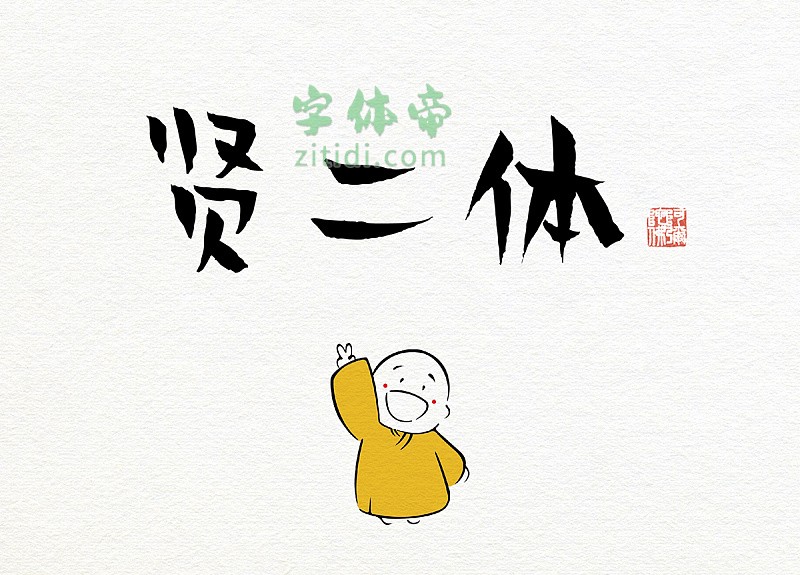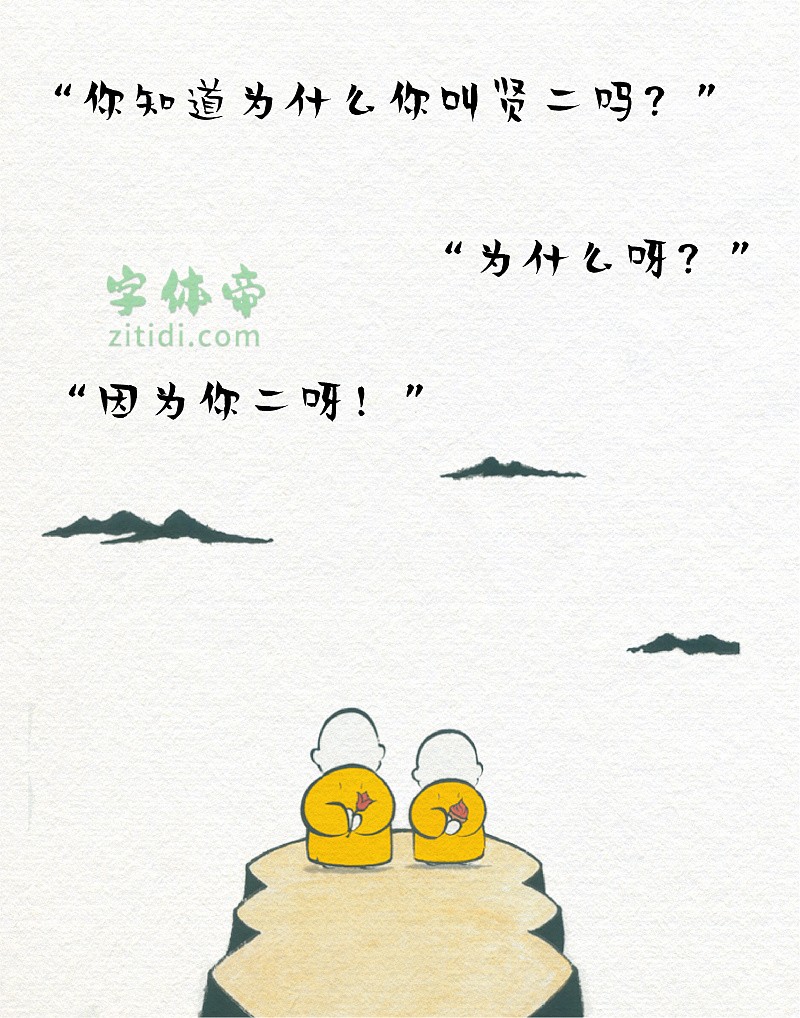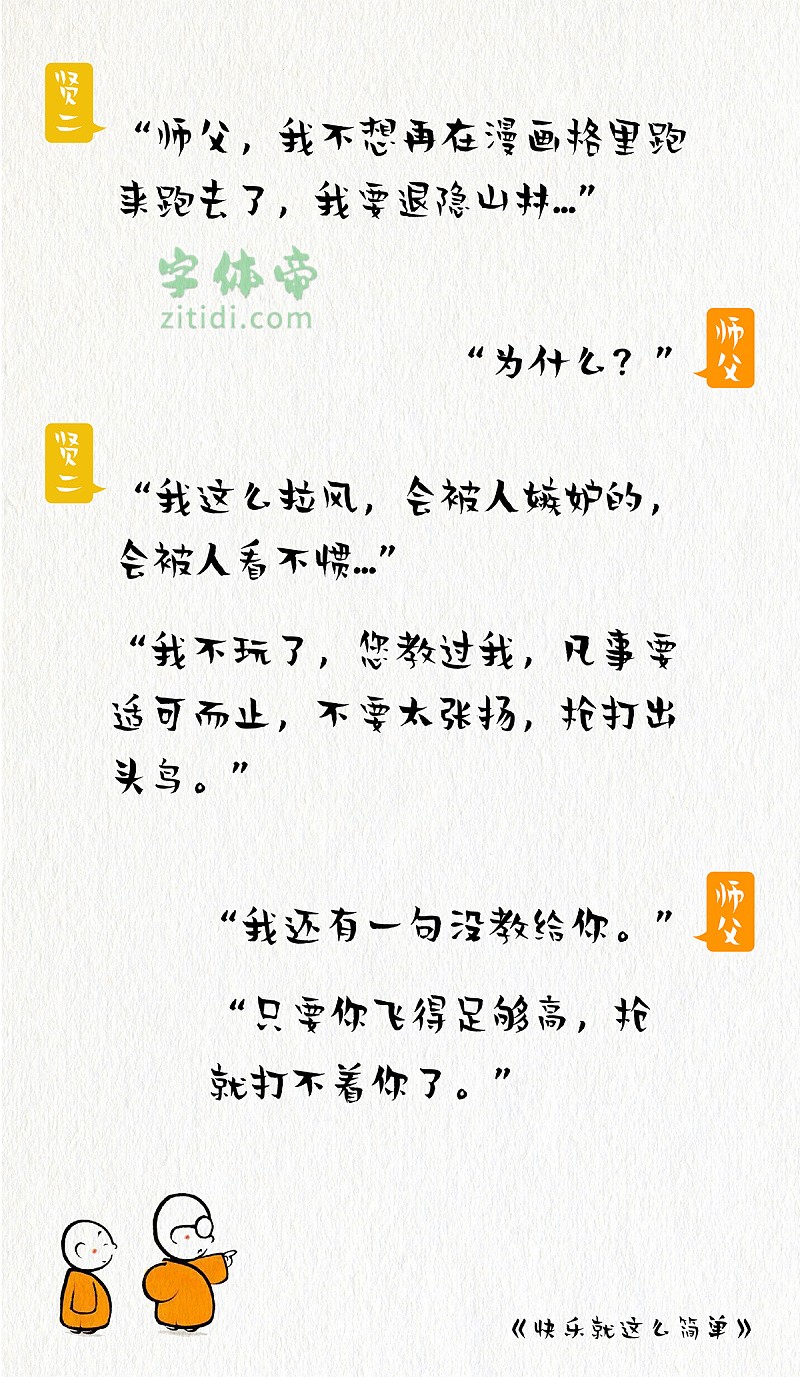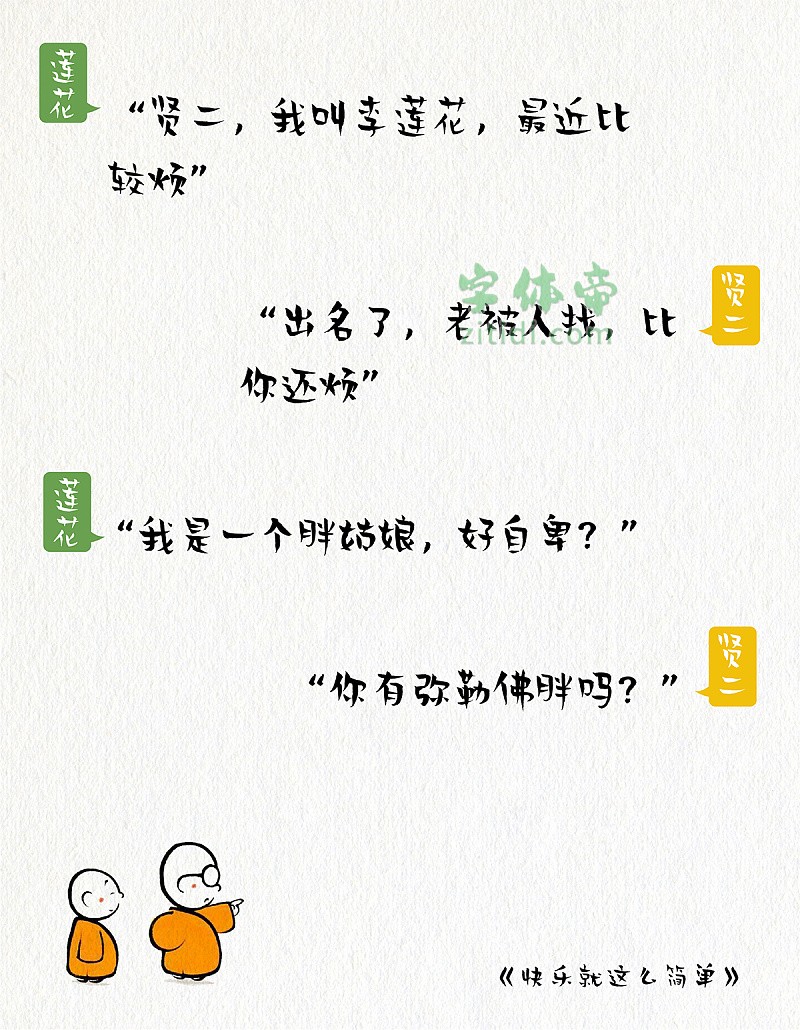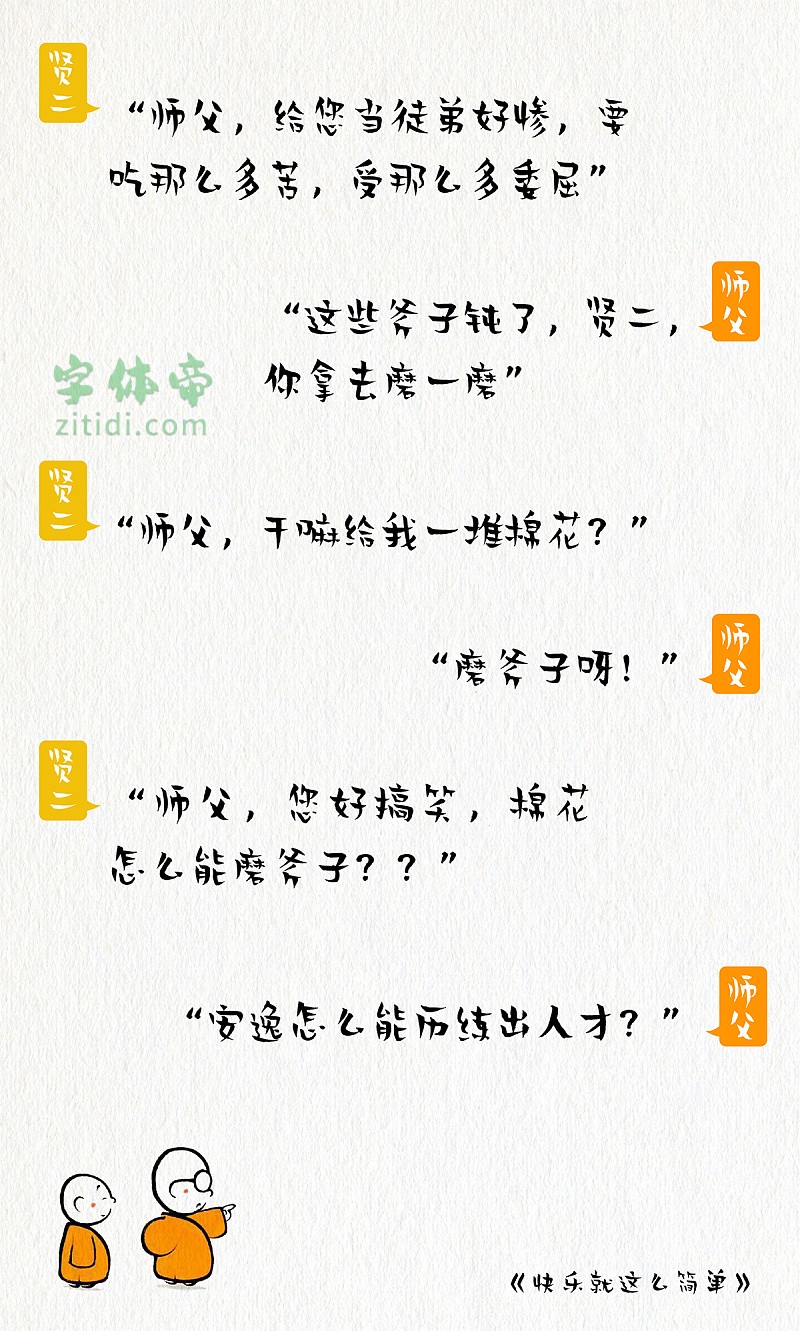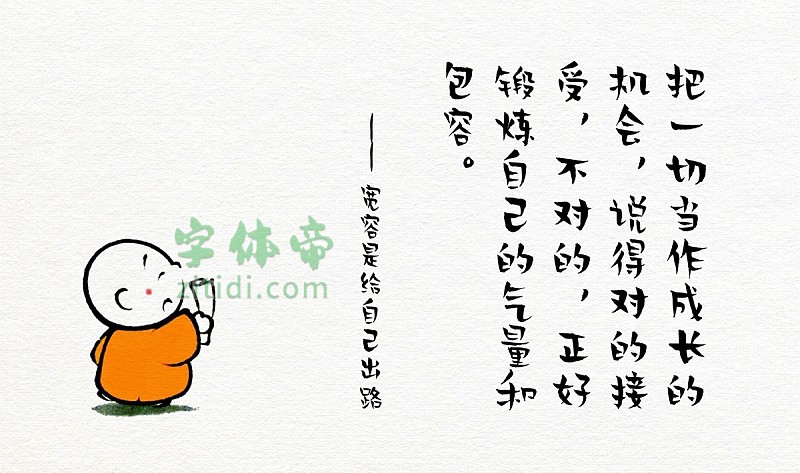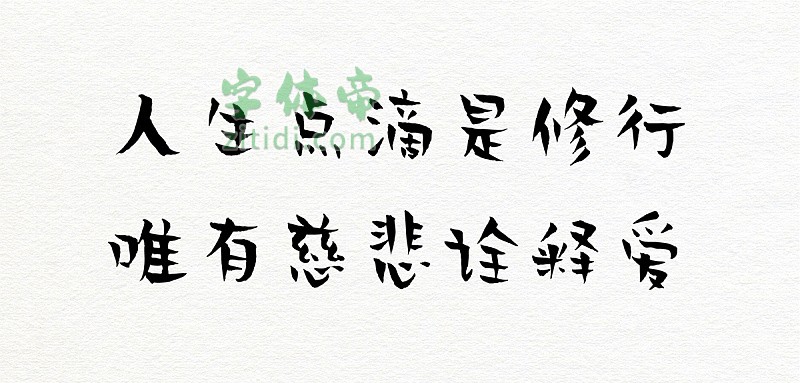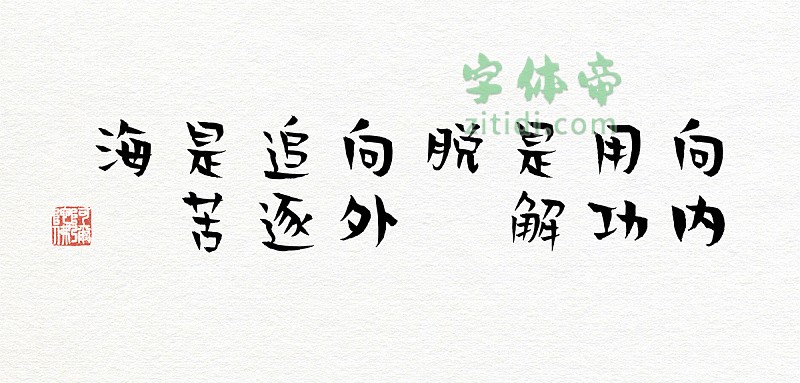
贤二体是北京龙泉寺动漫中心与汉仪字库联合推出的一款商用免费字体。 贤二体的字形偏长,起笔收笔锋利且粗细对比明显,笔画笨拙微带曲线感。字体组合结构松散,重心不稳,达到诙谐幽默,惹人喜爱的效果。
贤二体字形结构和笔画的特点恰好符合贤二小和尚的性格特点,与龙泉寺学诚法师所传达出的:“世俗生活里,人还是二一点比较好”如出一辙。
谁是贤二?
是不二寺的小和尚,一口气能吃十个冰激凌。他很聪明,但是又很懒惰,总是需要师父点拨。师父经常会讲一些饱含哲理的话语,帮助我们排解压力,告诉我们,其实,快乐就是这么简单。